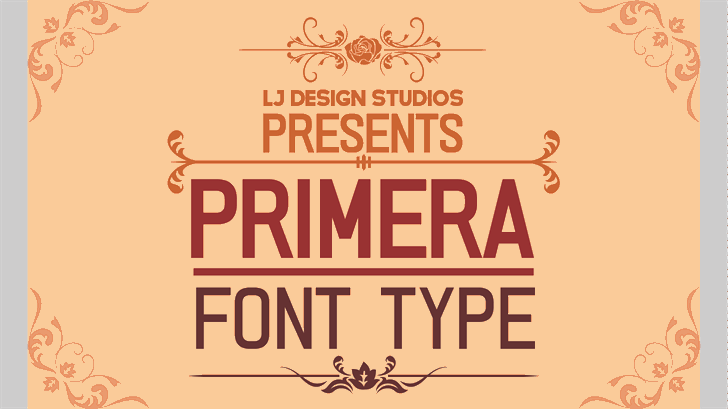
A PRIMERA é uma fonte não-latin criada pelo designer Hamilton, destinada a atender às necessidades específicas do uso comercial na comunicação e design digital. Esta font oferece um conjunto de letras, números e símbolos que podem ser facilmente integrados em diversos projetos gráficos, como logotipos, materiais de marketing ou texturas digitais. Com seu design moderno e elegante, a PRIMERA atende à sua missão de fornecer uma fonte não-latin poderosa e versátil. Se você está procurando por uma font que possa ser facilmente usada em projetos comerciais sem preocupações legais, esta é a font para você. Para acessar as letras e números bloqueadas para uso comercial, basta acessar http://ljdesignstudios.es.tl/PRIMERA.htm ou entrar em contato com os designers pelo email  – .